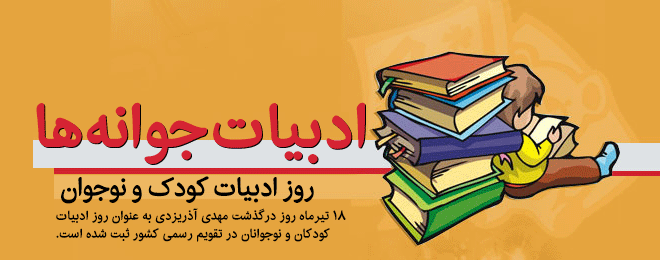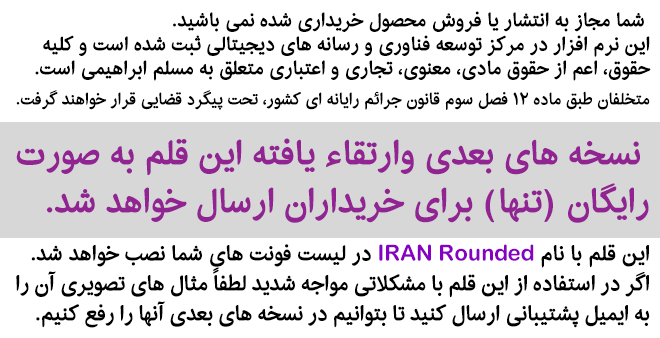
در میان فونت های موجود فارسی تعداد محدودی فونت فانتزی و نرم وجود دارد که از میان آن ها هیچکدام در سبک نسخ نیستند. اما قلم ایران گرد با حفظ ساختار نسخ ایرانی دارای ظاهر اصطلاحاً پفکی و فانتزی است. بنا براین در زمینه تبلیغات و بسته بندی مواد غذایی ، طنز و کودک و نوجوان می تواند کاربرد بسیاری داشته باشد.
شما با خرید این محصول نسخه های وب فونت را هم دریافت خواهید کرد. اگرچه به دلیل بولد بودن، وب فونت ایران گرد در اندازه کوچک چندان خوانایی نخواهد داشت اما در سایز بالا و برای نمایش عنوانها می توانید یک فونت منحصر به فرد باشید.
در این فونت از فونت مکمل انگلیسی Arial Rounded استفاده شده است تا در متنهای فارسی انگلیسی نیازی به تغییر فونت نداشته باشید.